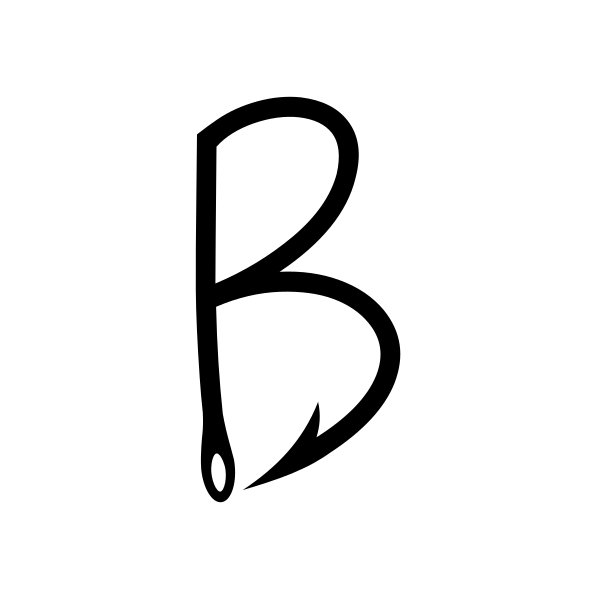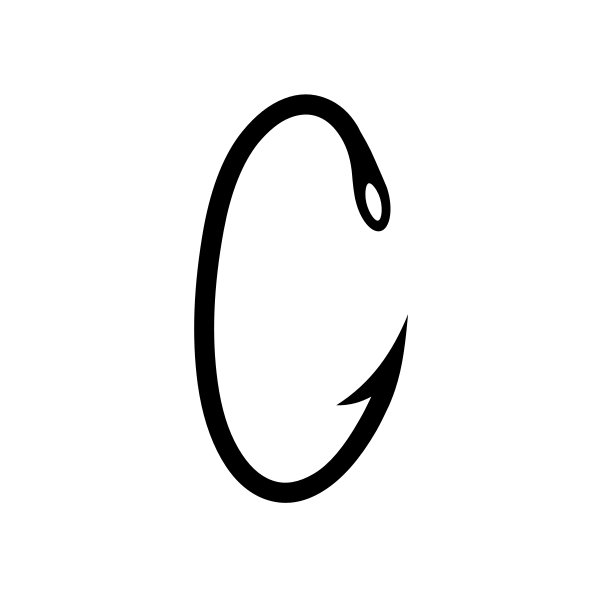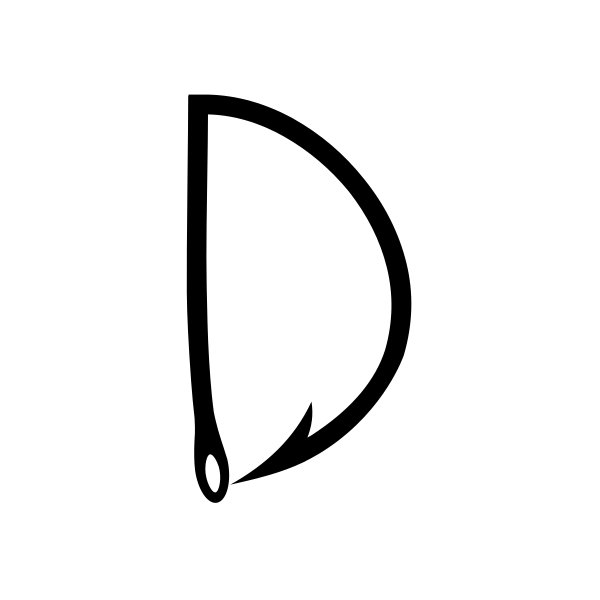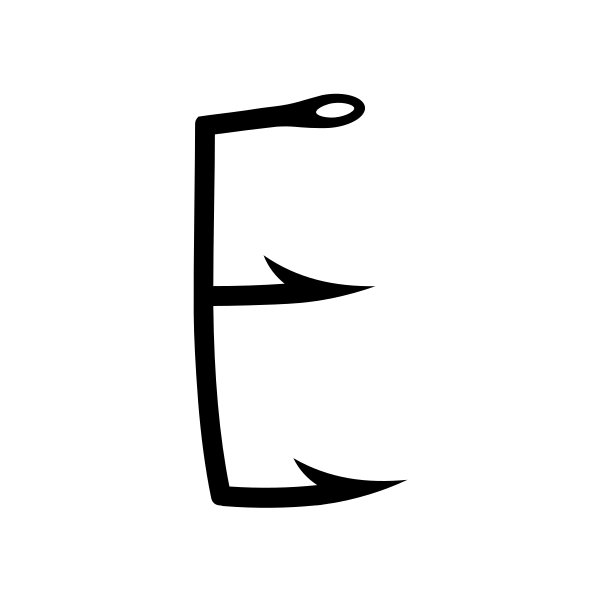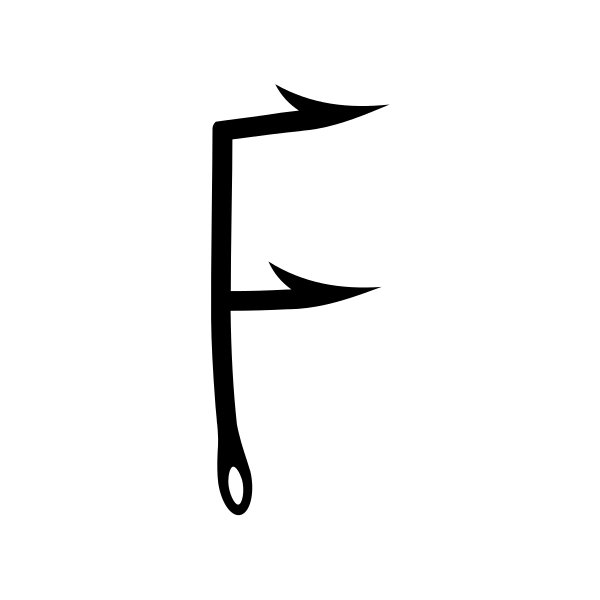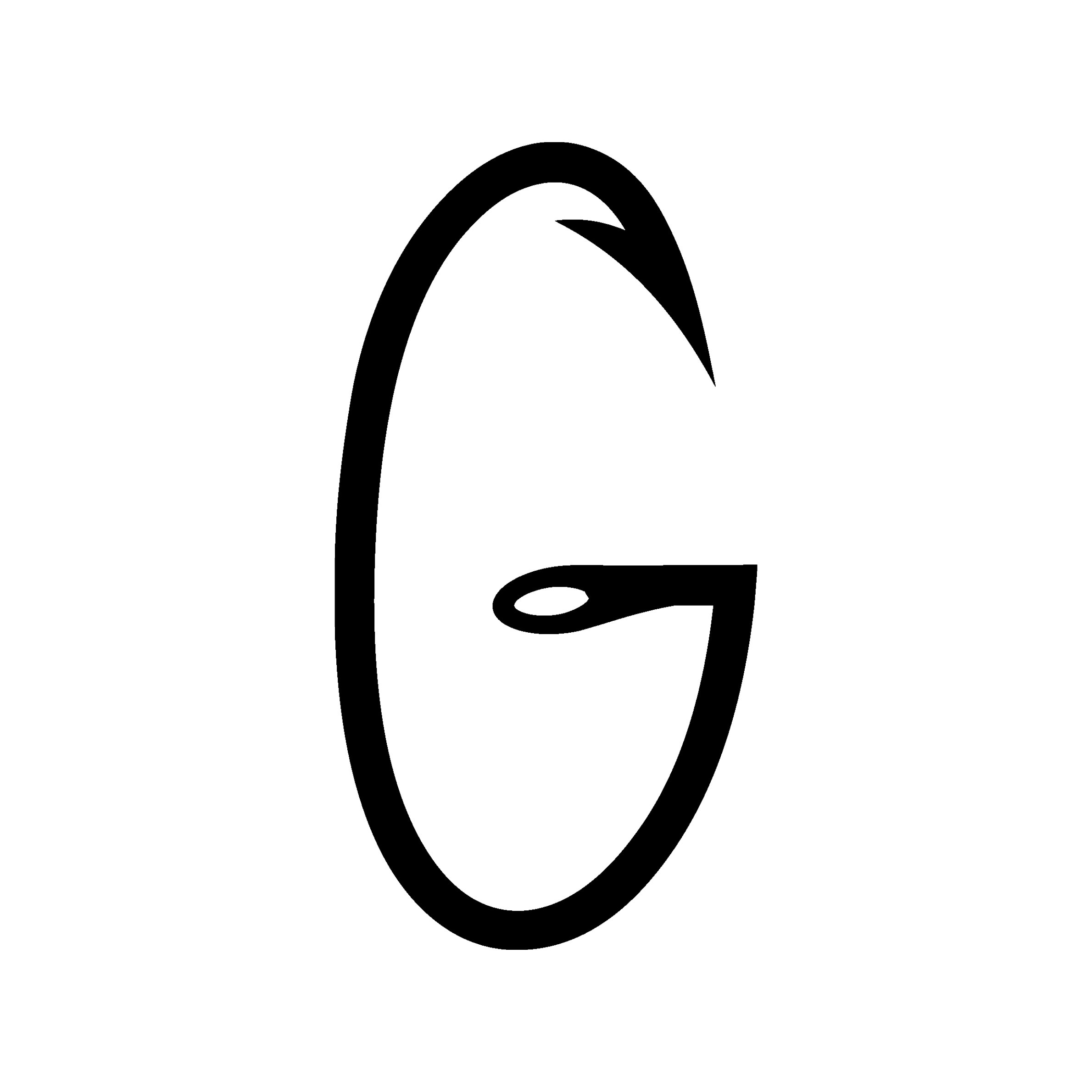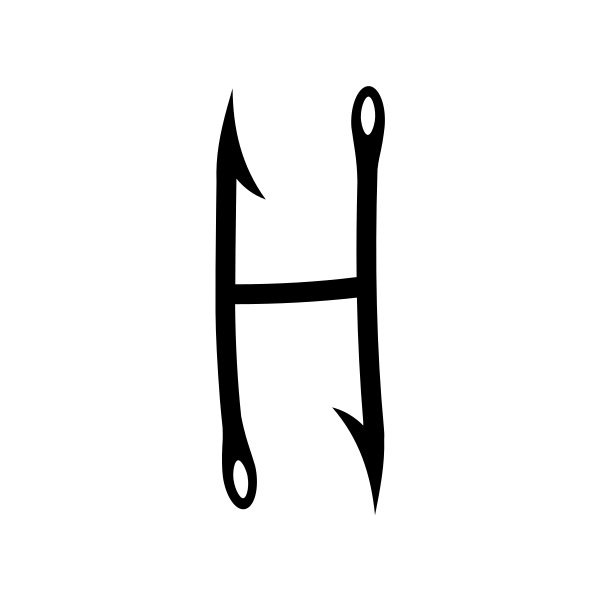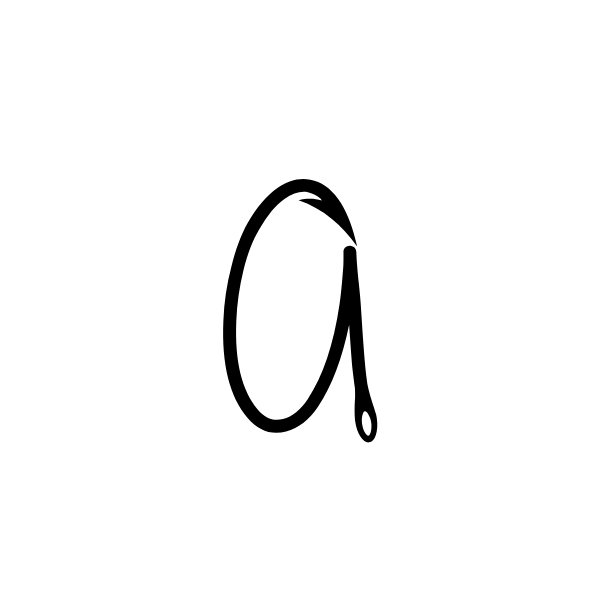
Fishing Font – Dekorative Angelhaken Schrift | Cricut-kompatibel
Fishing Font ist eine dekorative Großbuchstaben-Schrift mit markanten Angelhaken-Elementen in jedem Buchstaben. Die klaren Linien werden durch feine Hakenformen ergänzt, die an Köder, Schnur und Angelzubehör erinnern. Dadurch entsteht ein auffälliger, thematisch passender Look für Projekte rund um Angeln, Outdoor und Natur. Die Buchstaben sind deutlich lesbar und gleichzeitig verspielt gestaltet, wodurch sie sich sowohl für größere Überschriften als auch für kurze Namen oder Begriffe eignen.
Die Schrift wirkt handgezeichnet und individuell, ohne unruhig zu erscheinen. Sie passt ideal zu maritimen Motiven, Camping-Themen, Vereinsprojekten oder saisonalen Designs. Fishing Font verleiht jedem kreativen Vorhaben einen charakterstarken, rustikalen Stil mit klarer Wiedererkennung.